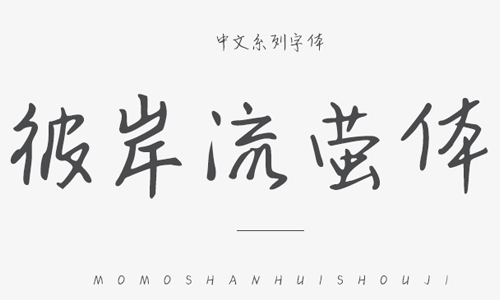
彼岸流螢體字體是一款擁有水筆手寫效果的藝術(shù)字體,夕殿下珠簾,流螢飛復(fù)息。長夜縫羅衣,思君此何極。——彼岸流螢體。本字體是在國家標準簡體字庫GB2312所包含6763漢字的基礎(chǔ)上,又增加了近200常用字,已經(jīng)覆蓋了大陸99.75%的漢字使用頻率,足以滿足日常需求。能夠應(yīng)用于文本裝潢、信息展示、網(wǎng)頁設(shè)計、篆刻制模、數(shù)據(jù)制作、裝潢設(shè)計、計算藝術(shù)設(shè)計、視覺設(shè)計、字帖等一切合法應(yīng)用場景,歡迎有需要的朋友前來下載使用。